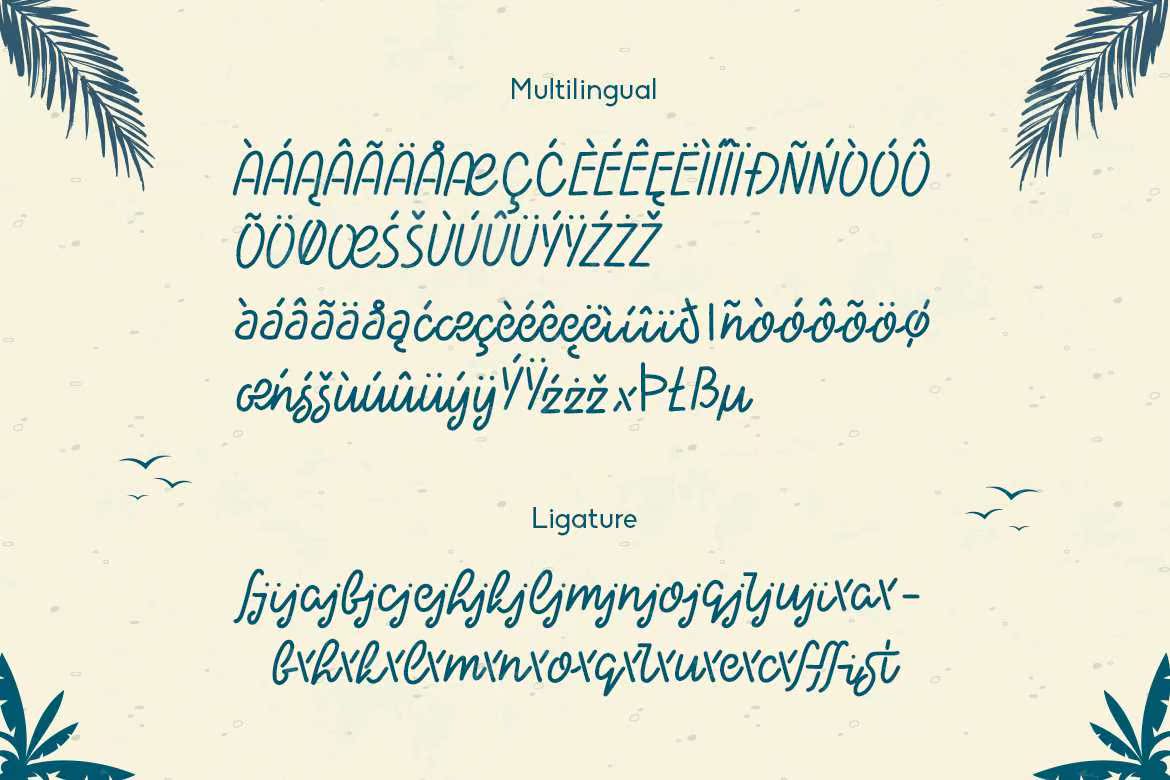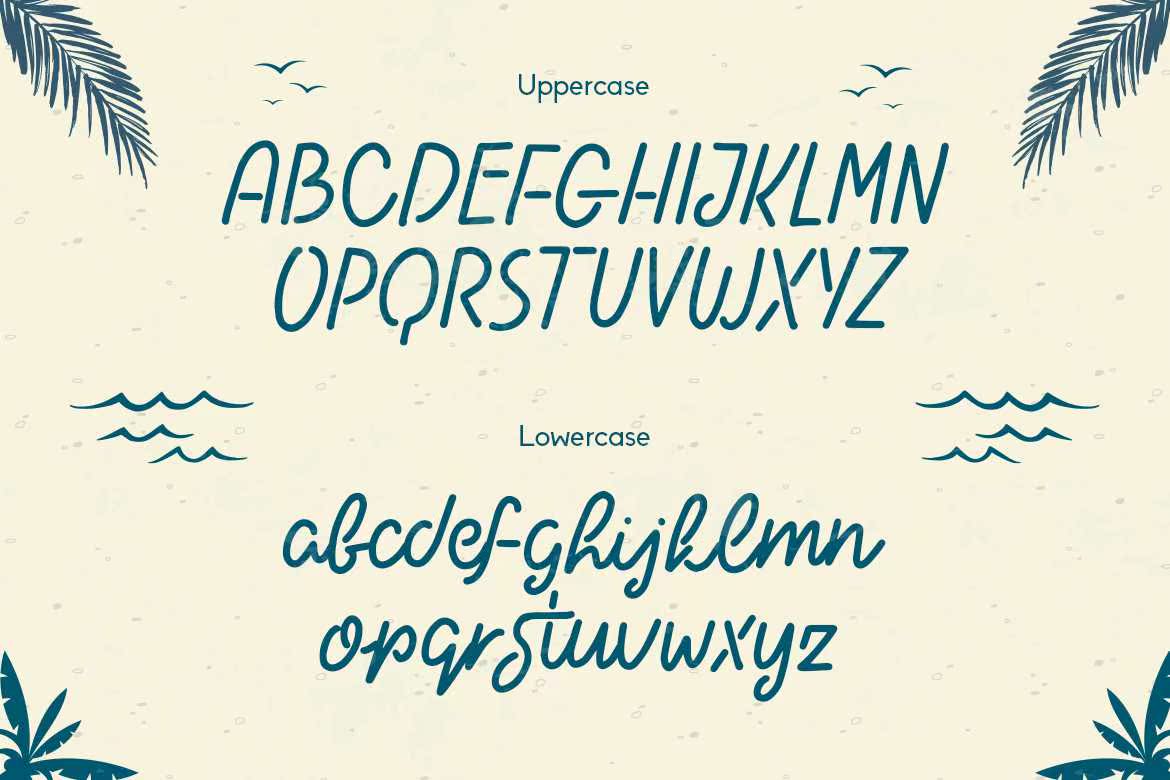
HaloHai是一款优雅的脚本字体,它将为您的设计带来美丽和伤害。它的灵感来自于摘要主题图和自然主题。HaloHai的品牌目的包括徽标、标签、标题、标题、产品、社交媒体、名片、报价、,和其他完整版本下载:HaloHai是一种优雅的脚本字体,将为您的设计带来美丽和伤害。它由总结主题图和主题、休闲和自然引发。HaloHai适用于品牌目的,包括徽标、标签、标题、标题、产品、社交媒体、名片、报价和其他完整版本下载: